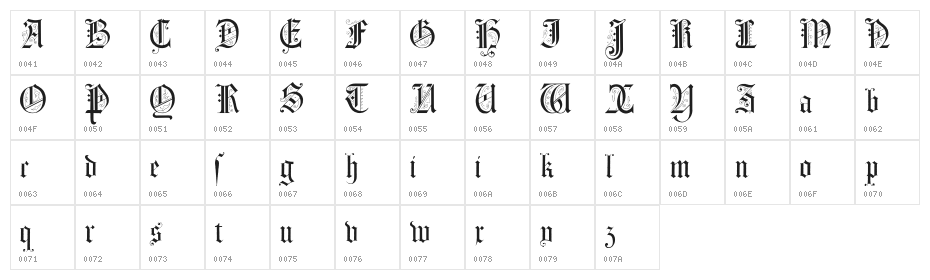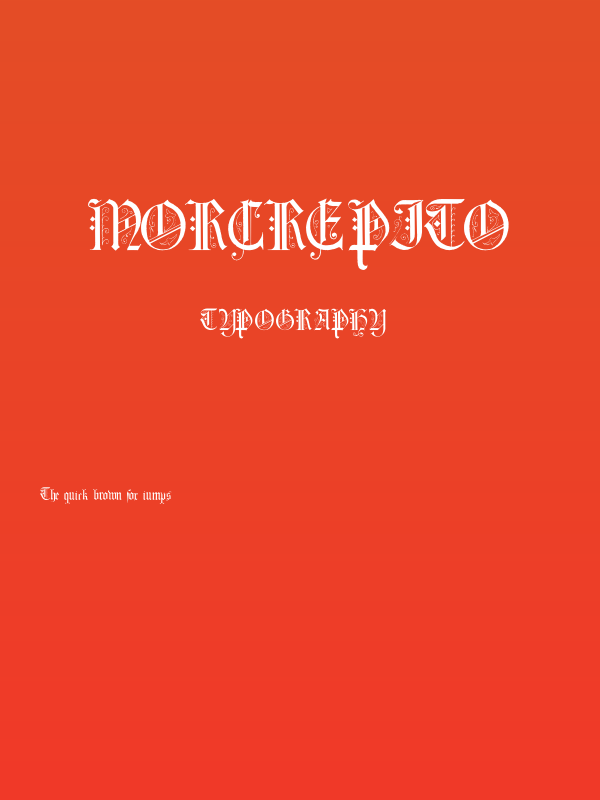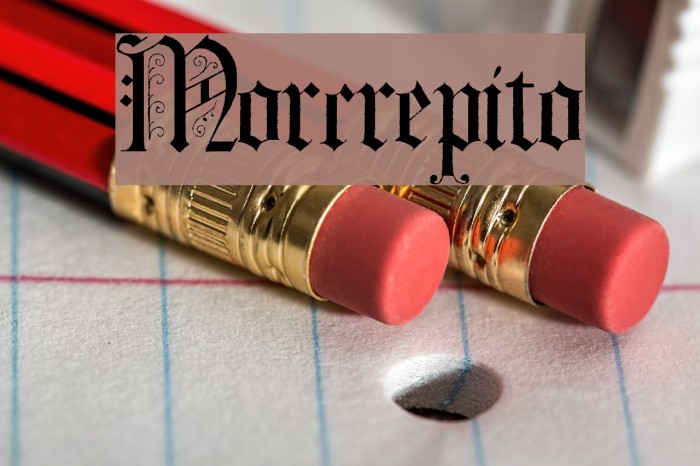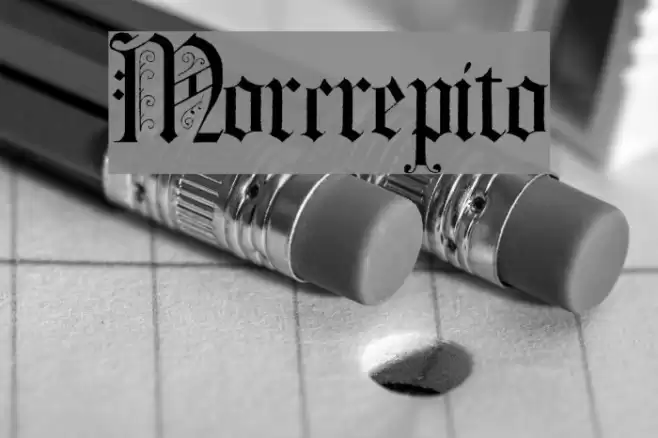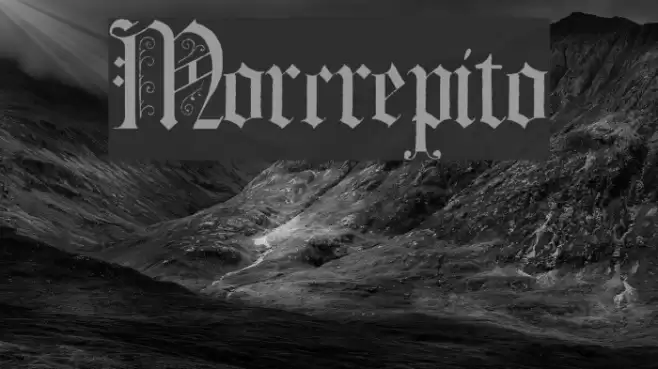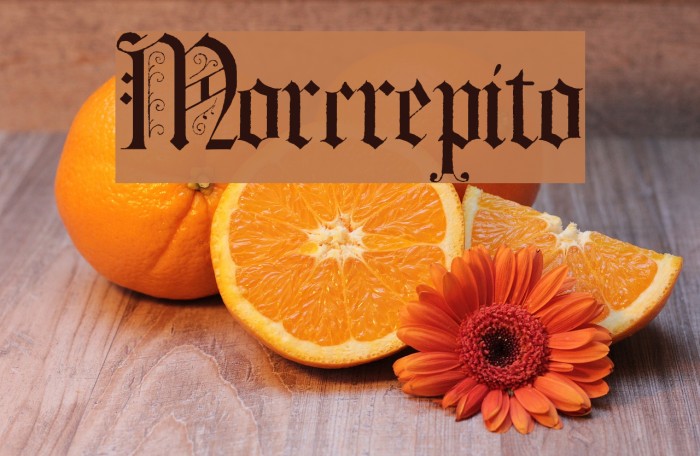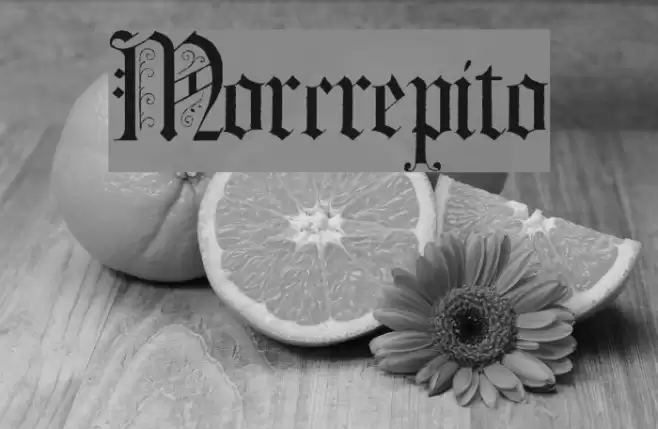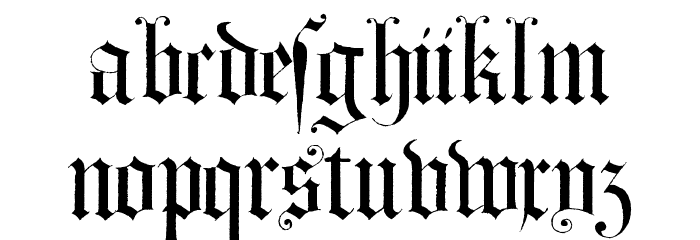
Morcrepito Font
✎ Gothic
| Общий стиль | Vintage |
| Область применения | Logos, Headlines, Decorative purposes |
| Рекомендуемые проекты | Ideal for projects requiring a historical or gothic touch, such as book covers, posters, or themed event invitations. |